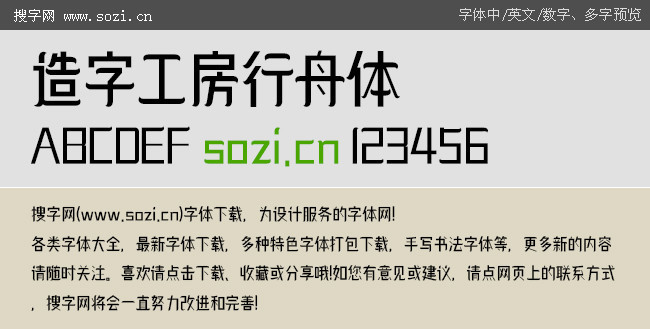
造字工房行舟體
搜字網(wǎng)給大家提供一款造字工房行舟體中文字體下載,造字工房行舟體整體風(fēng)格緊中見放,簡淡秀潤。字體中大量弧線的應(yīng)用,令其更顯婉轉(zhuǎn)流暢,字形舒展靈動,雍容古雅。筆畫粗中帶細(xì),錯落有致、收放有度,給人以酣暢瀟灑之感,有極強(qiáng)的視覺表現(xiàn)力。適用于大標(biāo)題、包裝設(shè)計、海報設(shè)計等應(yīng)用。(本字體為個人非商用版,如需要商用請聯(lián)系官方購買版權(quán))